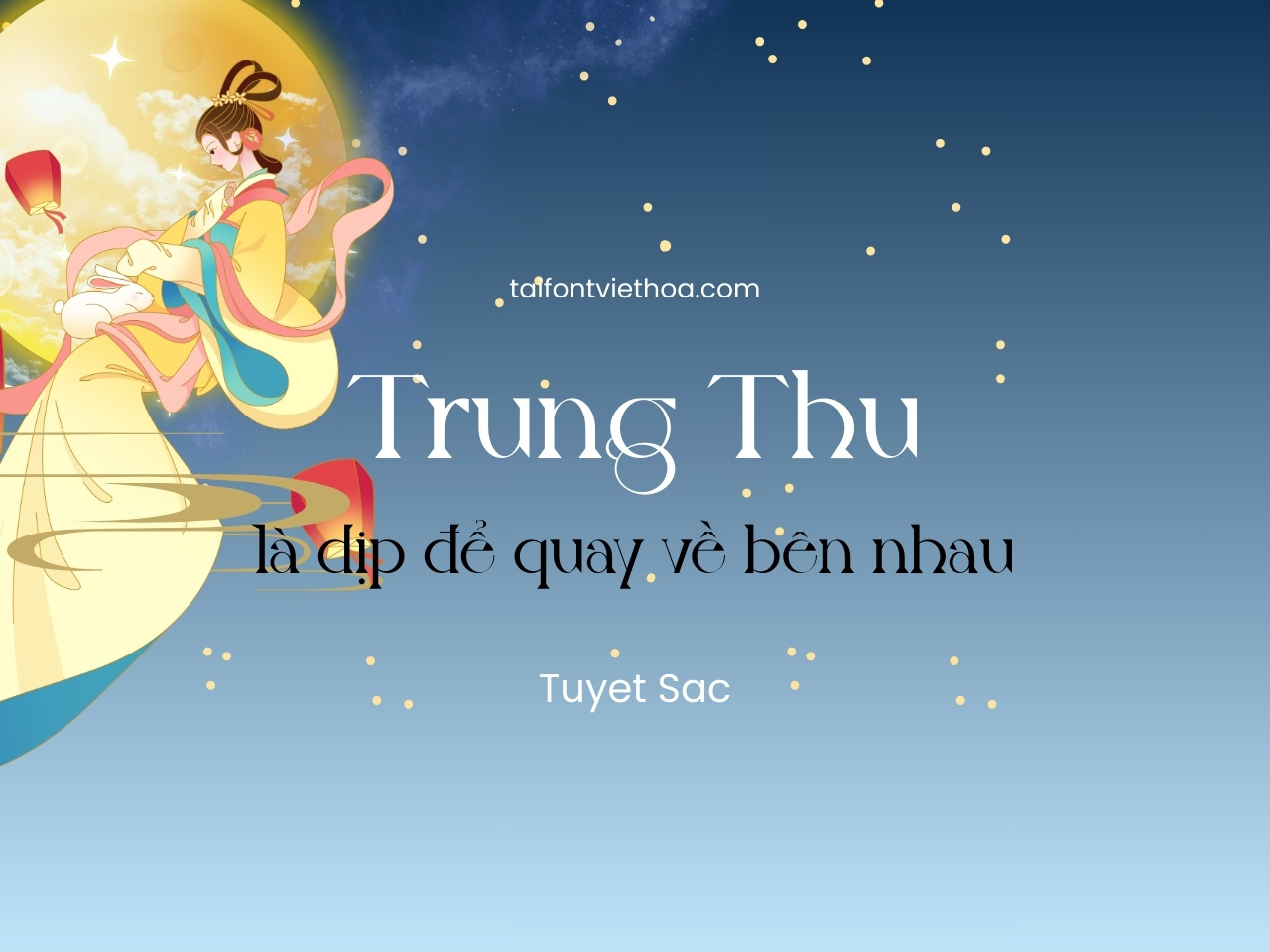
Font việt hóa Tuyệt Sắc Font Tiếng Việt
Tác giả Font: Cường Lưu, Linh Trần, Linh Cao
Giới thiệu về font Tuyệt Sắc
Font Tuyệt Sắc là một kiểu chữ serif pha trộn giữa phong cách thư pháp cổ điển và đường nét hiện đại, được thiết kế bởi nhóm tác giả người Việt: Cường Lưu, Linh Trần và Linh Cao. Phông chữ này không chỉ mang vẻ đẹp lãng mạn, cổ trang mà còn thể hiện sự duyên dáng, thanh thoát rất riêng biệt. Là một sản phẩm sáng tạo thuần Việt, Tuyệt Sắc không dựa trên nền tảng font quốc tế nào mà được phát triển từ đầu nhằm phục vụ nhu cầu thiết kế mang bản sắc Á Đông.
Font đã được nhóm tác giả Việt hóa hoàn chỉnh và công bố dưới dạng mở rộng đầy đủ, hỗ trợ tất cả dấu tiếng Việt, bao gồm cả hệ thống glyphs cho trình bày thư pháp mềm mại. Font hiện được taifontviethoa.com chọn lọc, kiểm định chất lượng và giới thiệu rộng rãi đến cộng đồng thiết kế Việt như một lựa chọn lý tưởng trong các dự án văn hóa, lễ hội hoặc thiết kế nghệ thuật truyền thống.
Đặc điểm thiết kế và ứng dụng thực tế
Tuyệt Sắc là sự kết hợp tinh tế giữa cấu trúc serif thanh lịch và những nét uốn lượn bay bổng của font thư pháp Việt. Các ký tự được thiết kế mềm mại nhưng rõ nét, với độ tương phản vừa phải giữa thân chữ và chân chữ. Nét chữ có độ nghiêng nhẹ, mang lại cảm giác chuyển động và mềm mại, rất phù hợp với các thiết kế trang trọng, lễ nghi hoặc nghệ thuật truyền thống. Bộ font bao gồm cả chữ hoa, chữ thường, cùng hệ glyphs tùy biến giúp tăng tính biểu cảm cho mỗi dòng chữ.
Font này phù hợp với nhiều ứng dụng như thiết kế thiệp Tết, poster phim cổ trang, bìa sách lịch sử, ấn phẩm văn hóa dân gian, sản phẩm quà tặng thủ công, hoặc branding cho thương hiệu mang bản sắc văn hóa. Ngoài ra, Tuyệt Sắc cũng là lựa chọn